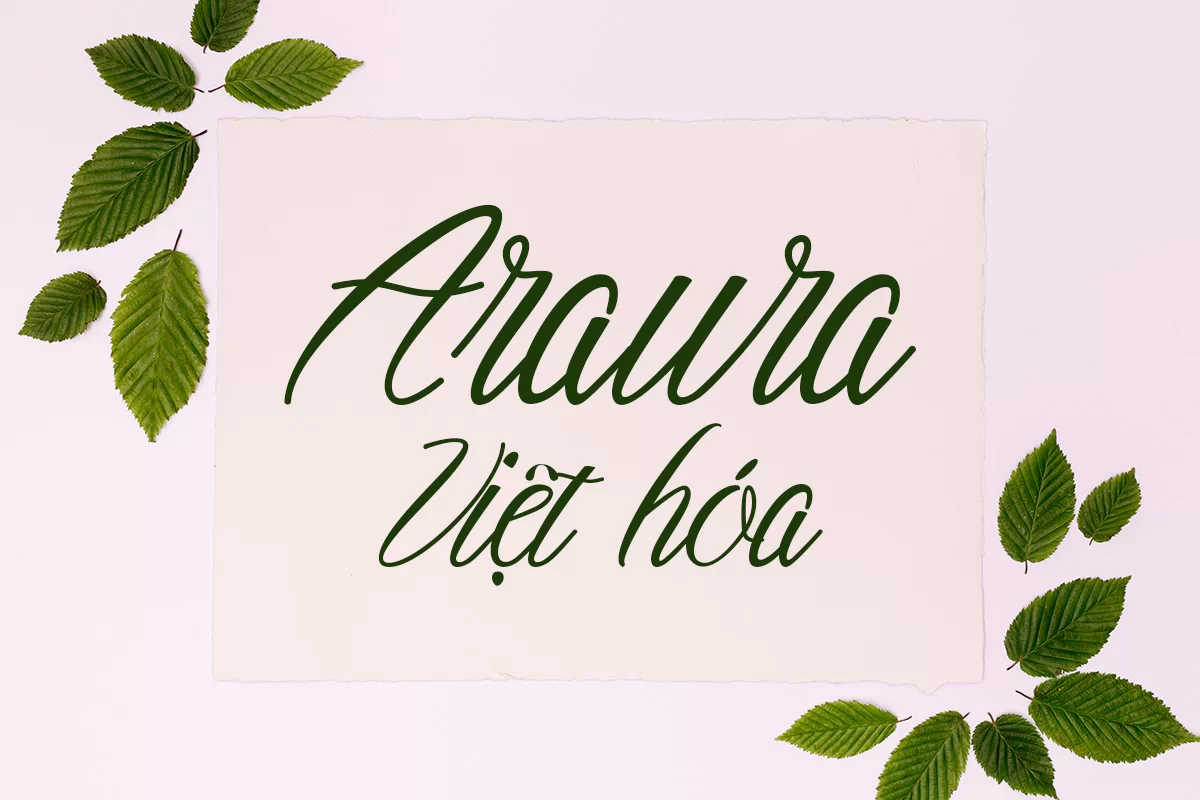
Araura Việt hóa là kiểu chữ script mềm mại với các nét bút lượn uyển chuyển, mang đậm cảm giác lãng mạn và tinh tế. Phiên bản Việt hóa được hỗ trợ đầy đủ dấu tiếng Việt, giúp bạn dễ dàng áp dụng trong các dự án thiết kế mang tính bản địa. Font đặc biệt phù hợp cho thiệp mời, poster nghệ thuật, thương hiệu thời trang, bao bì cao cấp và những thiết kế cần sự mềm mại, cuốn hút. Nét chữ thanh mảnh nhưng dứt khoát, tạo điểm nhấn sang trọng mà vẫn giữ được sự gần gũi, bay bổng.